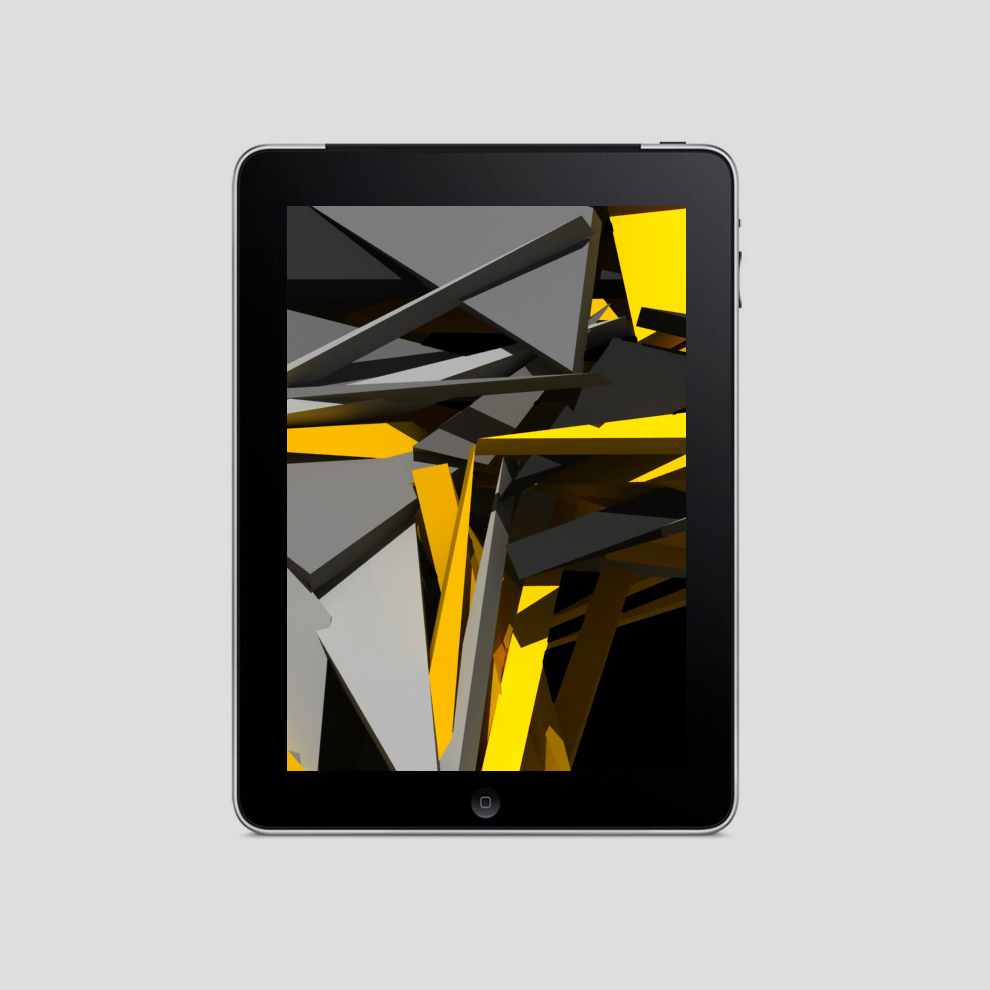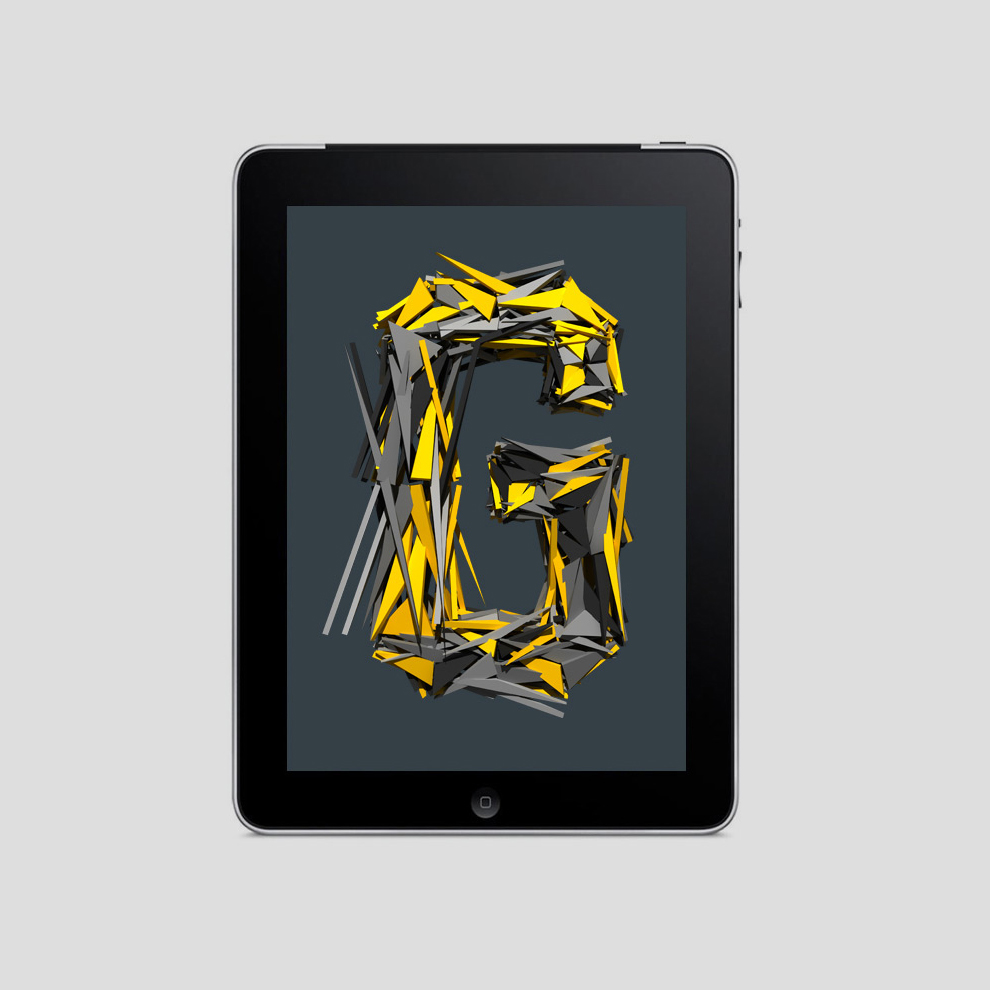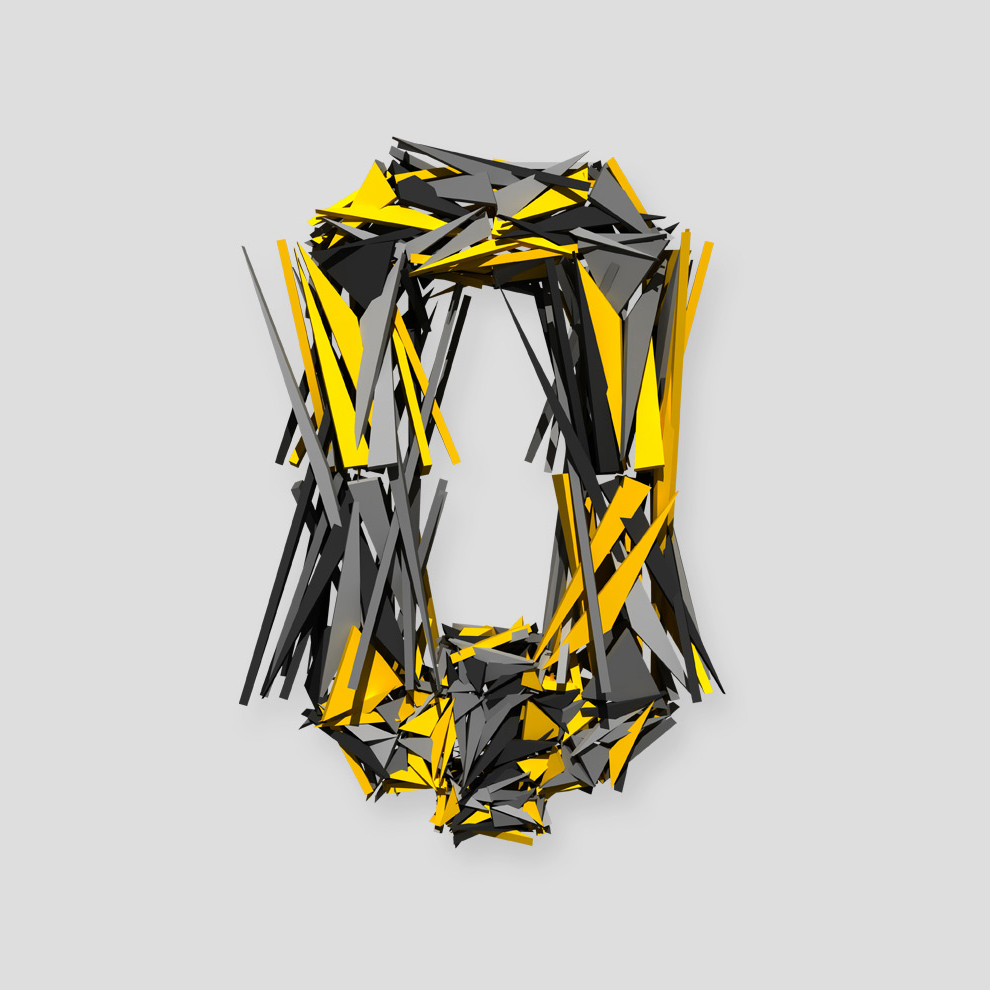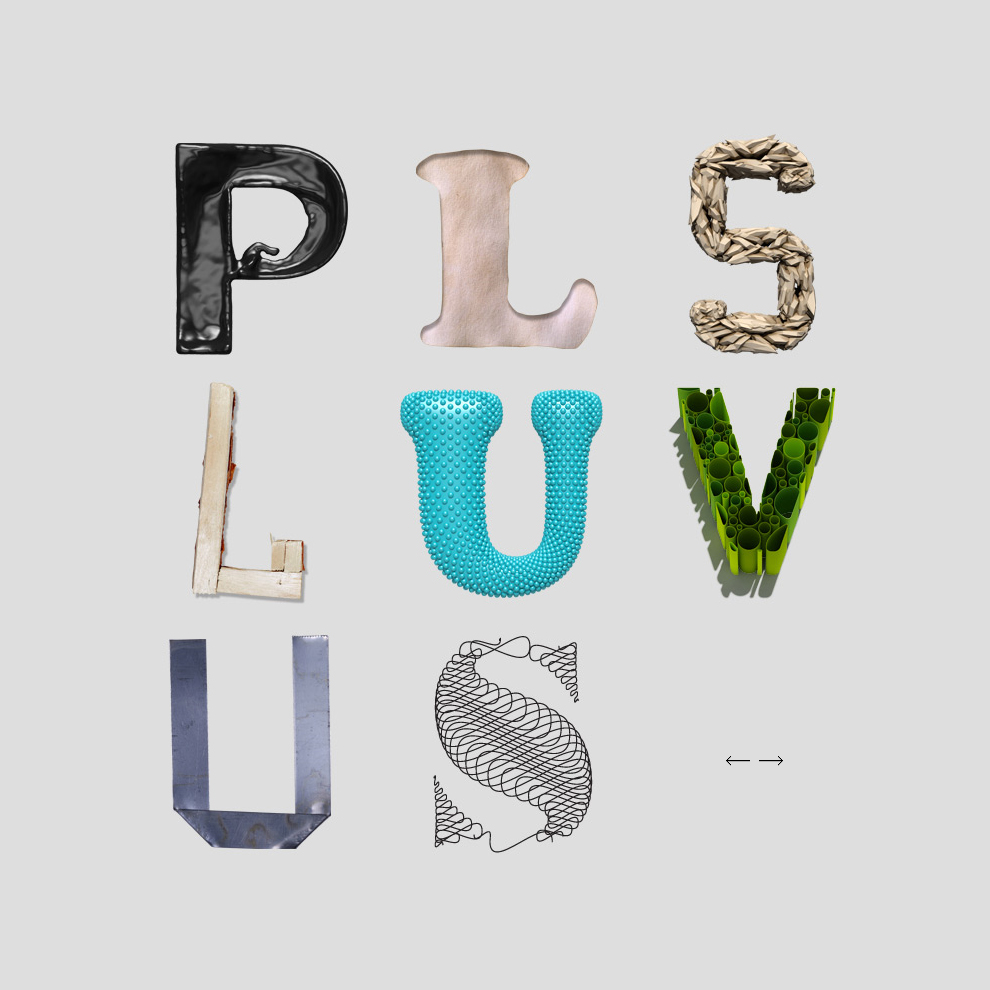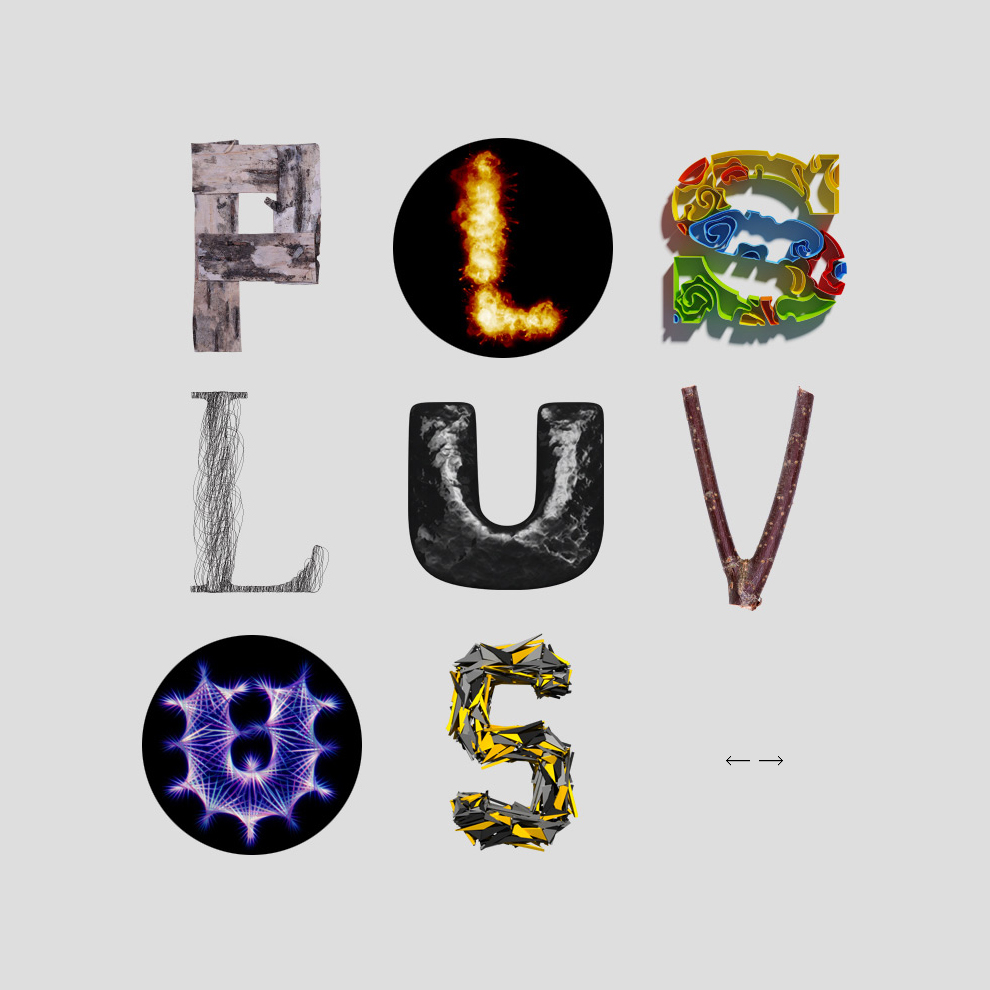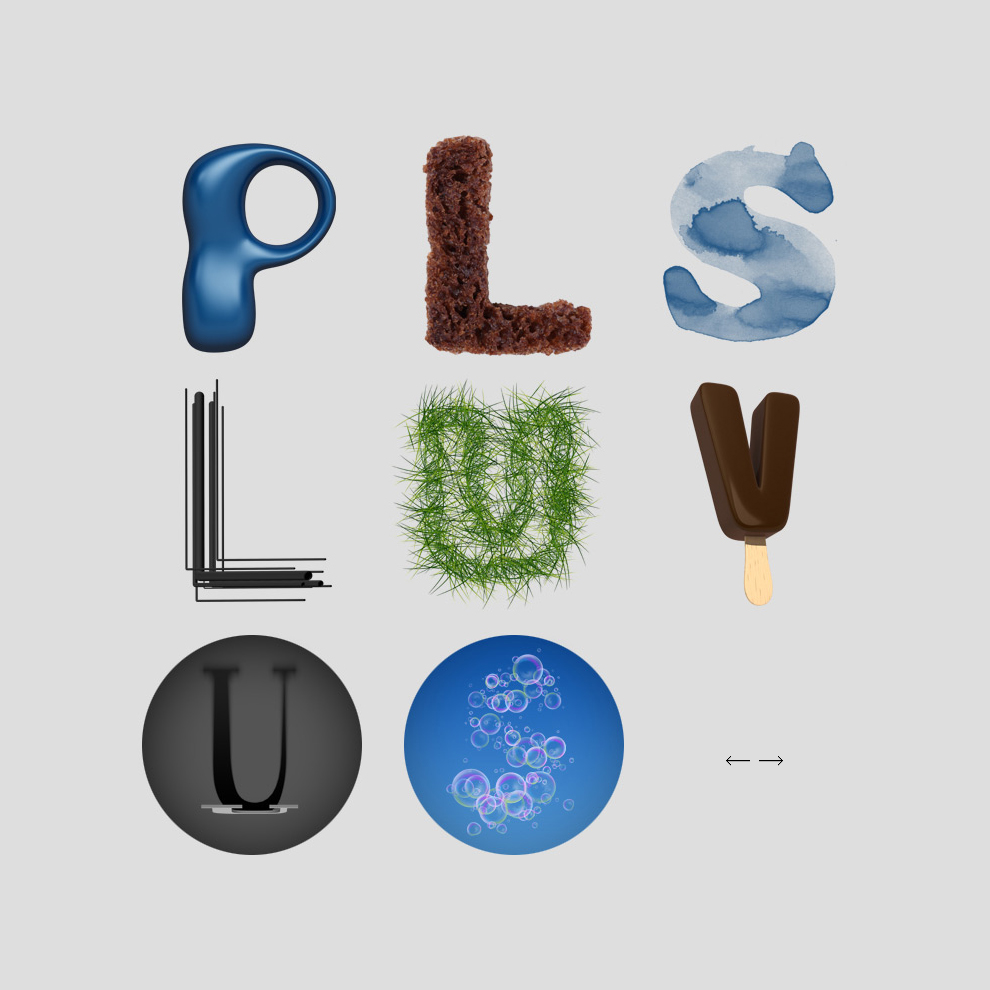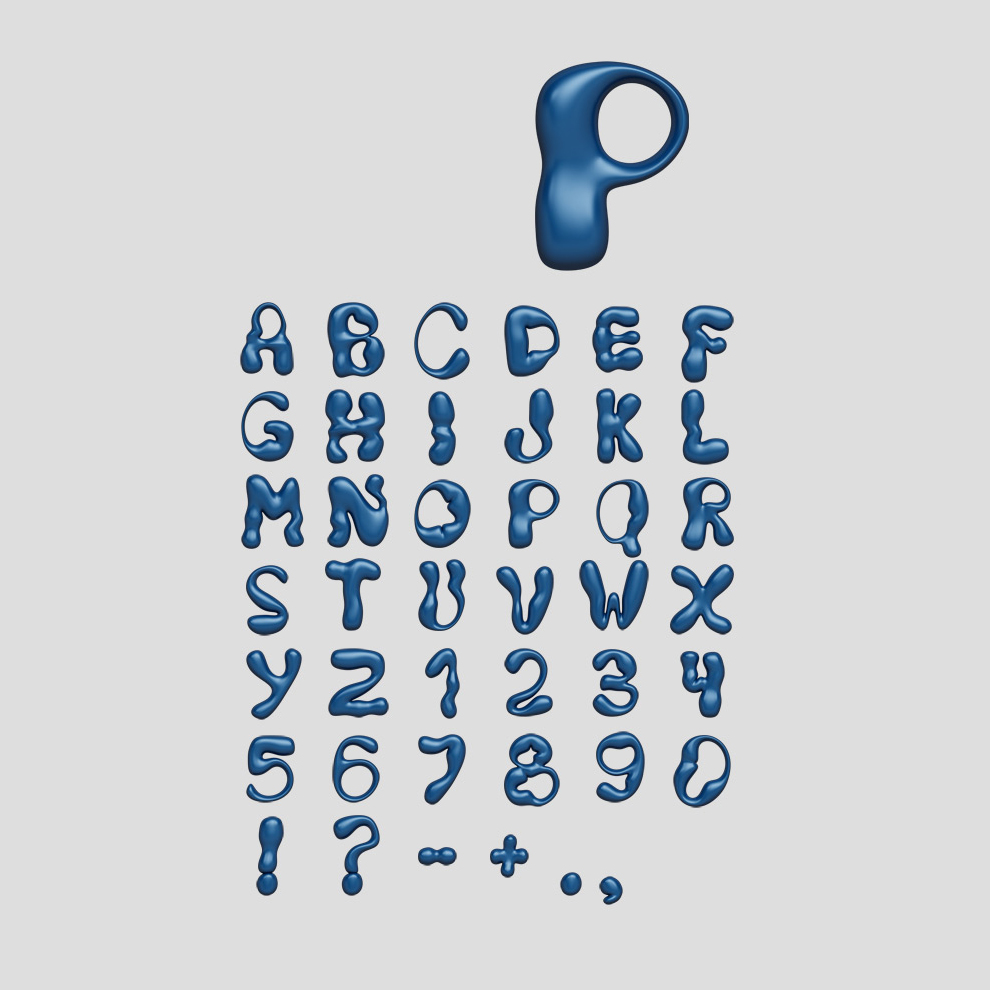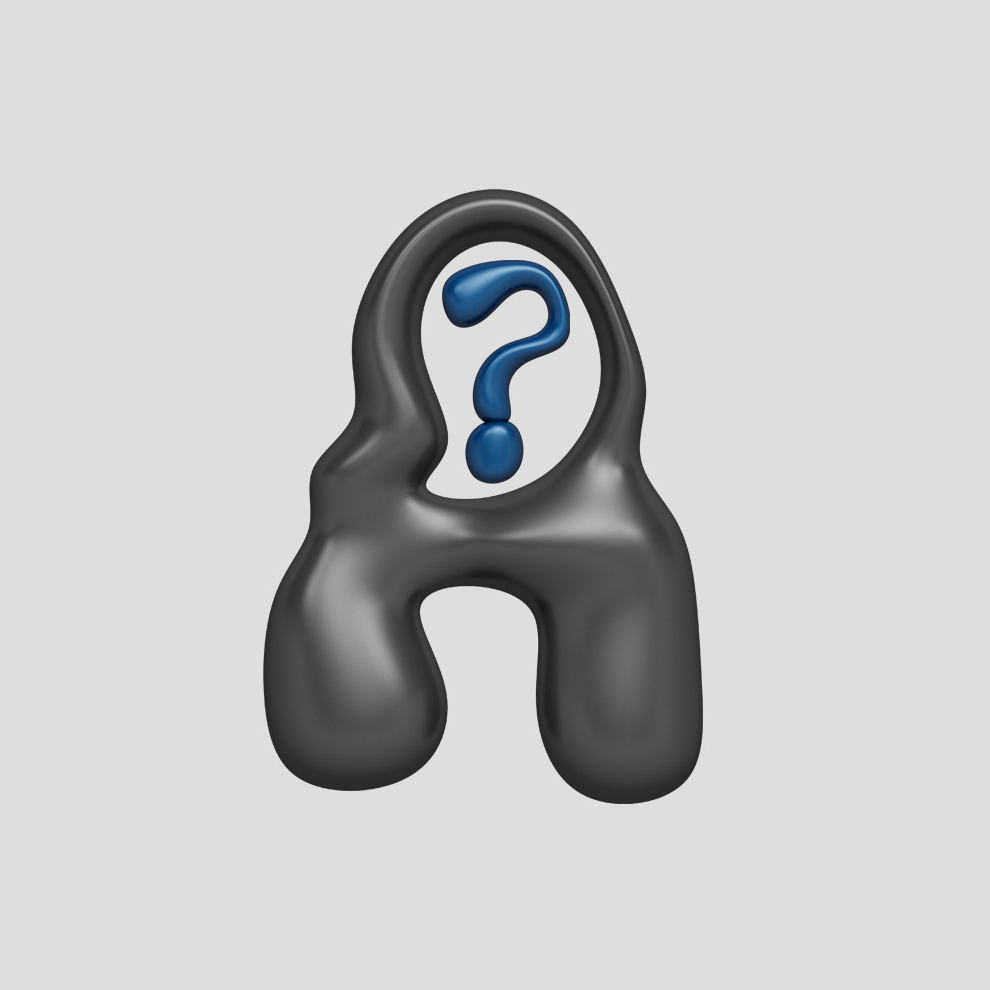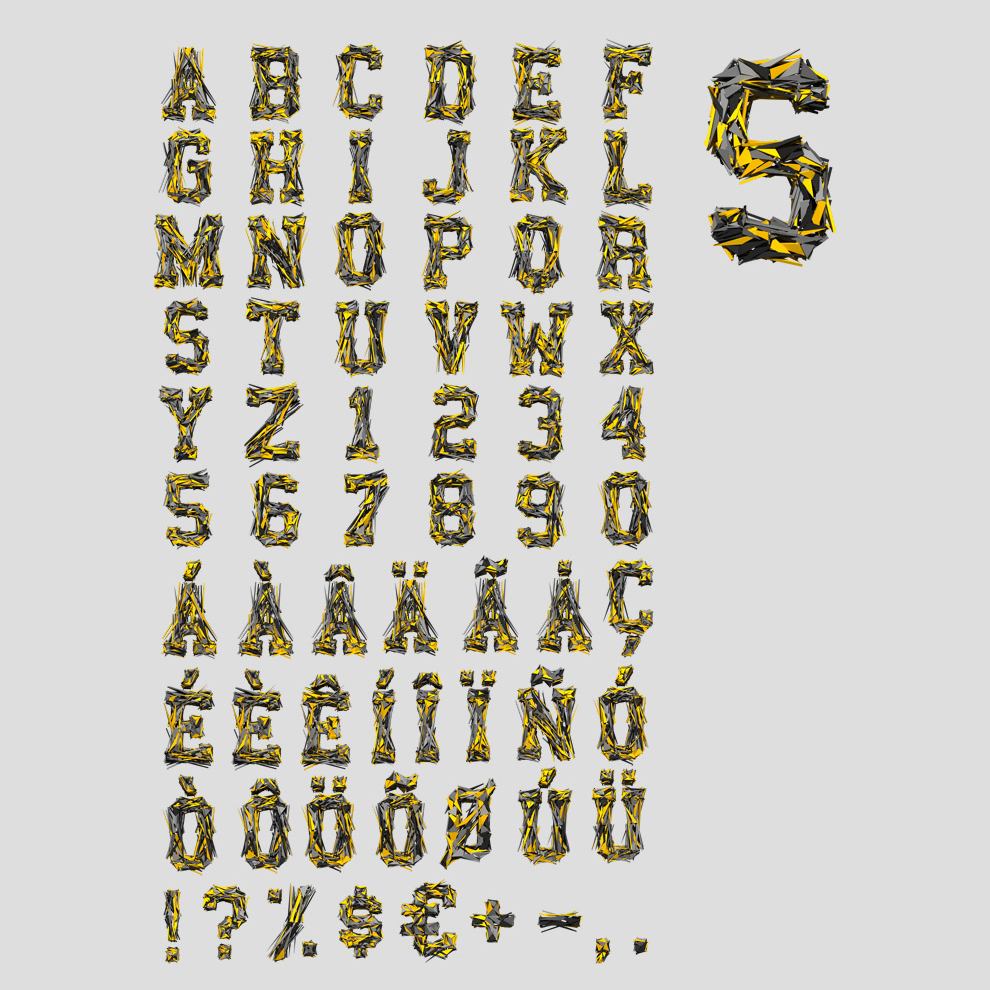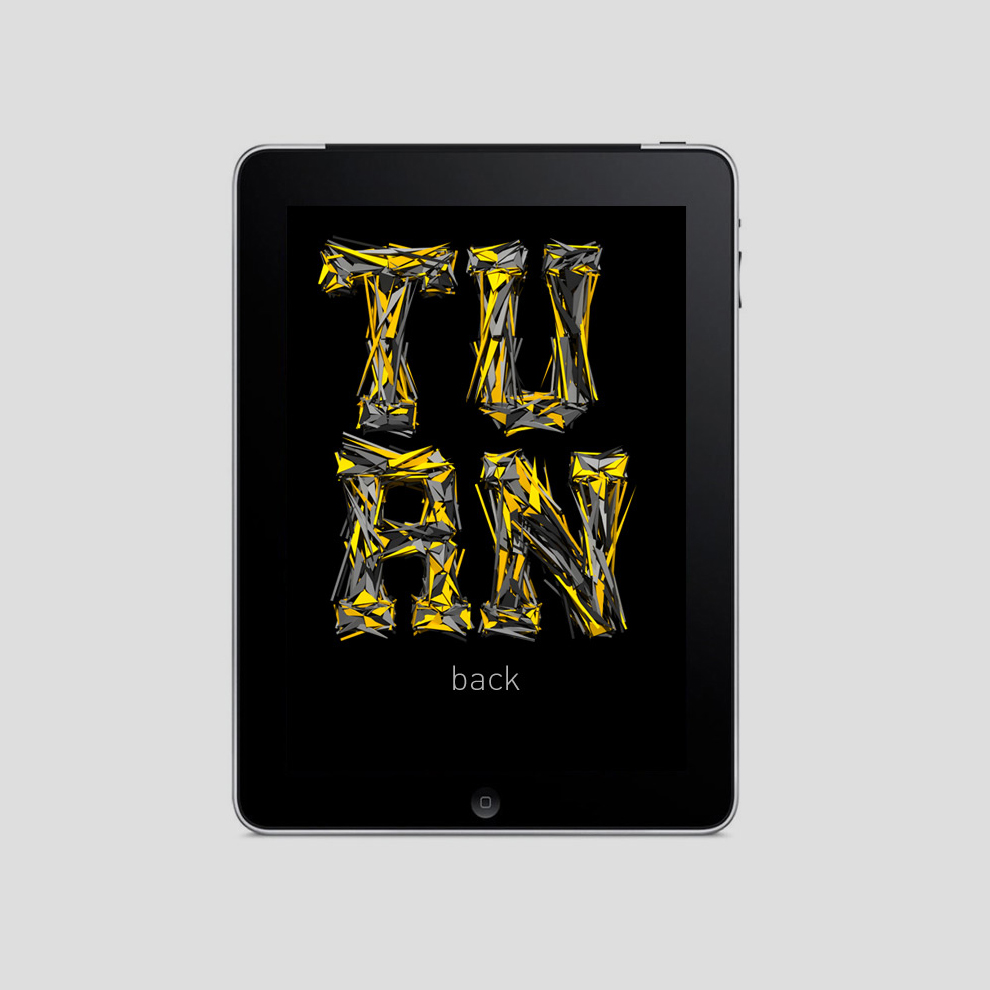
Hand Made Font
Hand made font est une agence de design graphique basée en Estonie. Elle a été fondée en 2008 par Vladimir Loginov et Maksim Loginov. Ils se sont spécialisés dans le développement de polices non traditionnelles.